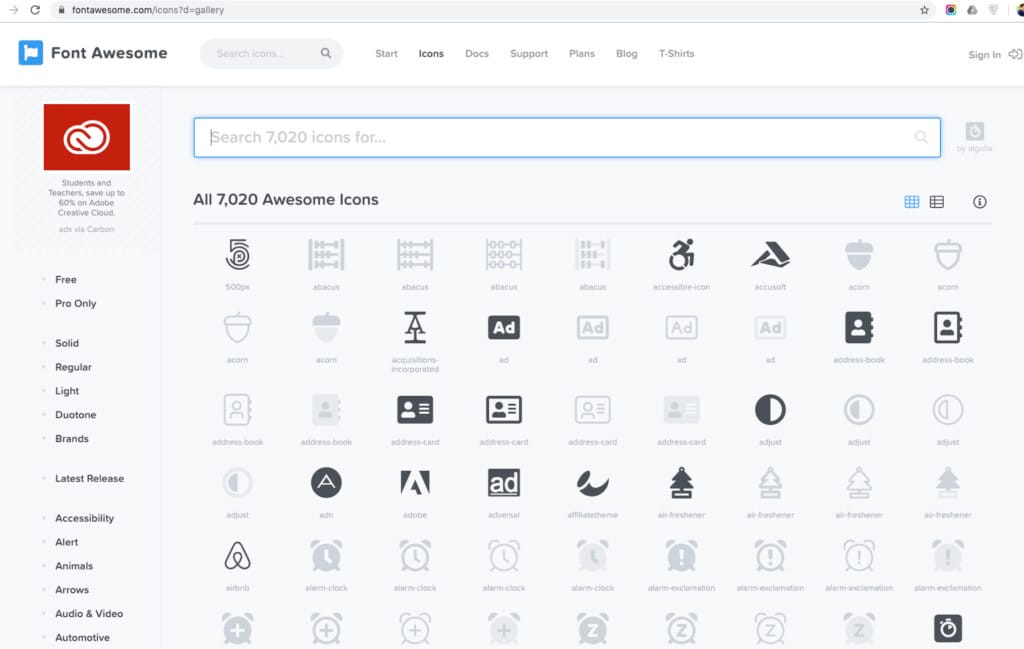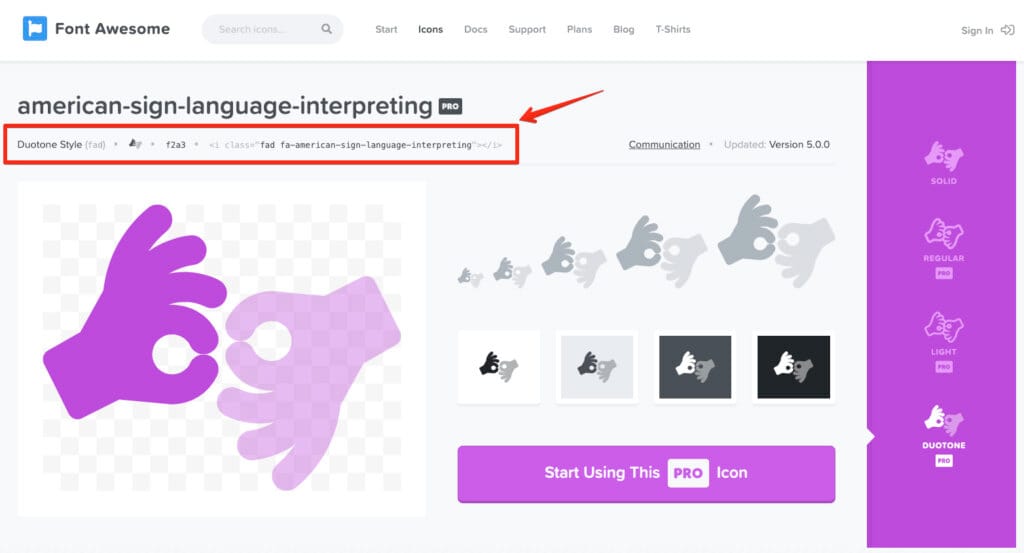
Bộ Font Awesome 5 Pro 5.15.4 cho Website mới nhất
Trong một layout website thường sẽ có những ICON giúp website đẹp và thân thiện hơn, và ngoài ra các ICON đó còn có tác dụng điều hướng người dùng.
Bộ Font Awesome 6 Pro đã ra mắt, nếu bạn quan tâm và muốn sử dụng cho website hoặc các thiết kế của mình thì có thể cập nhập thông tin và download từ link này: Font Awesome 6 Pro
Font Awesome 5 Pro là một thư viện chứa các font chữ ký hiệu hay sử dụng trong website. Font chữ ký hiệu ở đây chính là các icons mà ta thường hay sử dụng trong các layout website.
Trước đây để tạo các ICON đó ta phải thực hiện cắt chúng ra từ file PSD và dùng CSS để gán background hoặc dùng thẻ img để đưa ICON đó vào. Tuy nhiên hiện nay chúng ta đã có giải pháp khác đó là sử dụng Symbol Font (font chữ kiểu ký hiệu). Hiện nay có nhiều thư viện Symbol Font nhưng mạnh nhất và hay sử dụng nhất là Font Awesome vì nó đơn giản và dễ sử dụng.
Font Awesome được xây dựng thành nhiều định dạng file font khác nhau như file otf, eot, ttf, woff, svg, … Vì vậy bạn dễ dàng đưa vào sử dụng và hầu hết các hệ điều hành máy tính hiện nay đều chạy được.
Ngoài các icons thông thường ra thì bạn có thể tạo các icons động bằng cách kết hợp với CSS3.
Nếu bạn sử dụng Bootstrap để xây dựng CSS cho website thì sẽ dễ dàng nhận thấy sự cần thiết của Font Awesome bởi vì chúng kết hợp với nhau khá là tốt và tạo ra các sản phẩm khá là bắt mắt.
Hướng dẫn sử dụng Font Awesome
Đối với Duotone Icons mới nhất.
Cũng như các anh em của nó Duotone Icons sử dụng class fad làm prefix. Bạn có thể truy cập link để lấy list icon và code.
Version Font Awesome 5.15.4 Released August 4, 2021
• Đã thêm các biểu tượng mới liên quan đến COVID-19.
• Đã thêm khả năng chỉ định ID mask và ID tiêu đề cho SVG với JS cho phép các công cụ kiểm tra ảnh chụp nhanh nhận được kết quả có thể dự đoán được khi thực hiện kiểm tra.
• Đặt hiển thị phông chữ rõ ràng để chặn những cảnh báo hiển thị phông chữ trong các công cụ như Lighthouse.
• Đã sửa lỗi phiên bản 4 font face khai báo thuộc tính shim src có cảnh báo về định dạng tệp phông chữ không chính xác.
• Đã sửa tên họ phông chữ thành ‘Font Awesome 5 Free’ cho các bộ dụng cụ miễn phí khi sử dụng các yếu tố giả.
• Tính năng phát hiện xung đột
• Đã xóa biểu tượng tripadvisor theo yêu cầu của Tripadvisor
• Đã tạo font-family khớp với chữ hoa chữ thường cho phiên bản SVG + JavaScript của Font Awesome
Version Font Awesome 5.15.3 Released March 16, 2021
Giúp phổ biến về các khuyến nghị vệ sinh và các sáng kiến khác để chống lại COVID-19! Sử dụng các biểu tượng này trong các dấu hiệu, lời nhắc, ứng dụng theo dõi, v.v.
Version Font Awesome 5.15.2 Released January 13, 2021
• Đã thêm các biểu tượng mới liên quan đến COVID-19.
• Biểu tượng thương hiệu mới deezer, edge-inherit, google-pay, rush, tiktok và unsplash.
• Đã cập nhật biểu tượng thương hiệu bandcamp, google-plus, tripadvisor và yahoo
• Đã thêm các biểu tượng thương hiệu được tài trợ bởi guild, innosoft, instalod, hive, ns8 ,opus-deploy, perbyte, unsharted, watchman-monitor và wodu
• Đã xóa biểu tượng adobe theo yêu cầu của Adobe
• Cập nhật biểu tượng thương hiệu rocketchat
• Tính năng phát hiện xung đột hiện bao gồm Bộ dụng cụ khi kiểm tra xung đột
Version Font Awesome 5.15.1 Released October 5, 2020
• Đã thêm các biểu tượng mới liên quan đến COVID-19.
• Đã sửa tên phông chữ thành ‘Font Awesome 5 Free’ cho các bộ dụng cụ miễn phí khi sử dụng
• Biểu tượng thương hiệu mới deezer, edge-legacy, google-pay, rust, tiktok, and unsplash.
• Đã cập nhật biểu tượng thương hiệu bandcamp, google-plus, tripadvisor và yahoo
• Tính năng bao gồm Bộ dụng cụ phát hiện xung đột hiện
Version Font Awesome 5.14 Released July 15, 2020
Các phiên bản này bao gồm 126 biểu tượng mới!